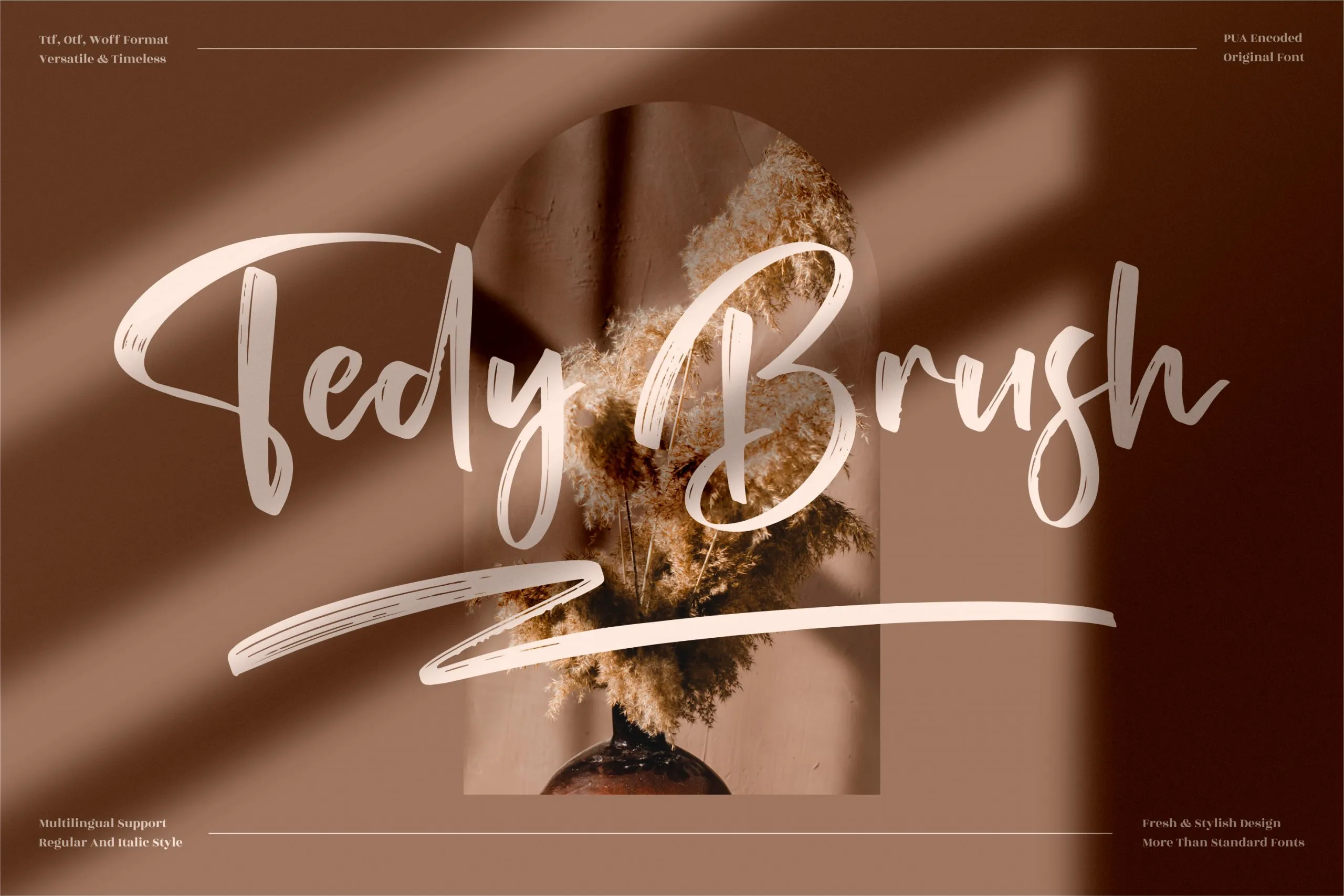
Tedy Brush Font – Download Grátis
Esta é uma fonte desenhada a mão que se ajusta perfeitamente para uma variedade de projetos criativos. Ela faz seu caminho entre logos e marcas, design de móveis de casa, embalagens de produtos, tigelas de café, cartazes, sacolas de compras, cartões de mensagens, anúncios personalizados, capas de livros, cartões de visita, convites, cartões de agradecimento, etiquetas e até mesmo para imagens fotográficas. Suas linhas suaves e espontâneas fornecerão um toque especial a qualquer trabalho que você está criando. Seja ele uma camiseta personalizada para o seu próximo evento único ou capa de livro elegante, Tedy Brush Font proporcionará aquele toque único e autêntico que seu projeto merece.